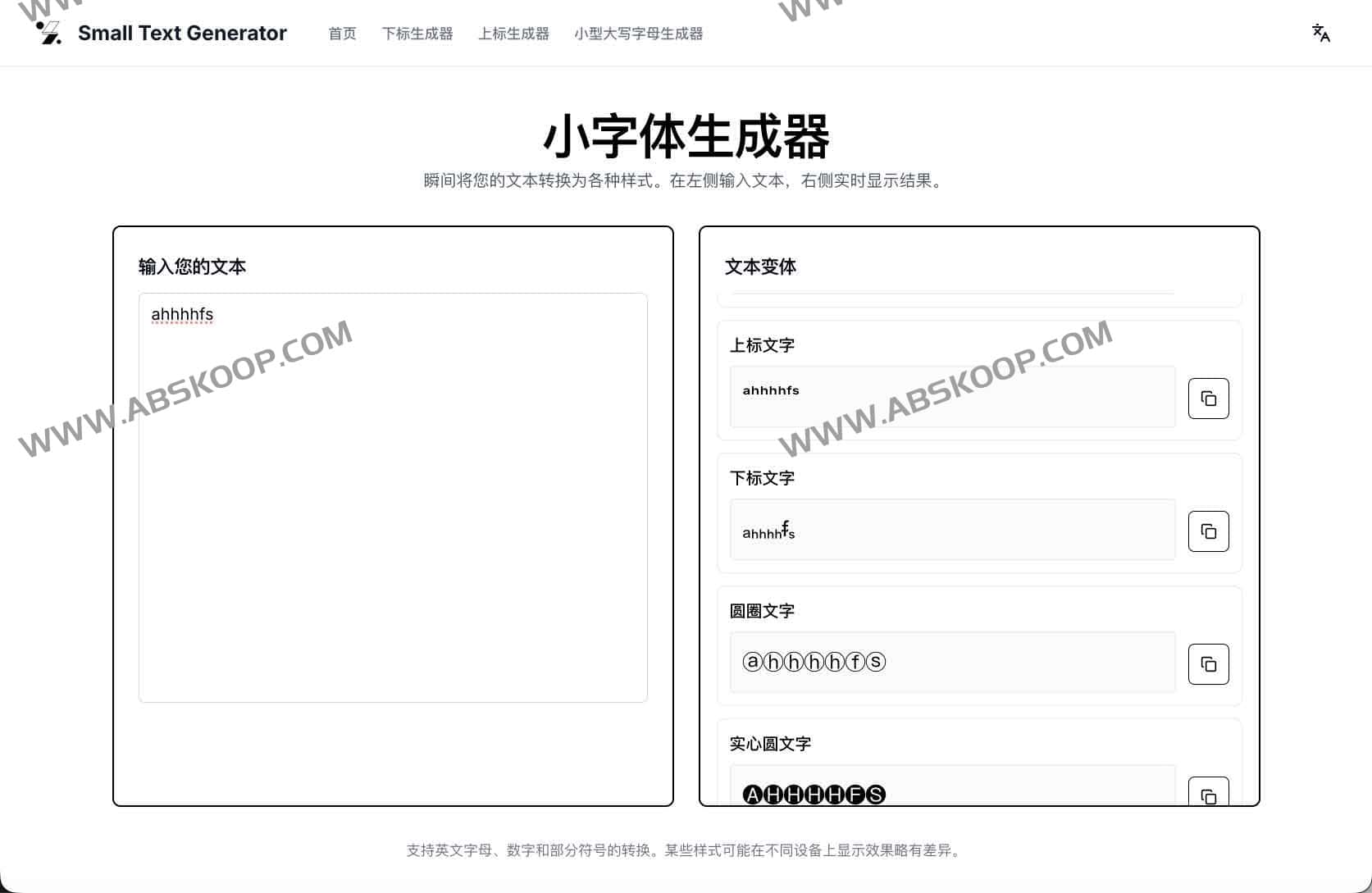
Small Text Generator 是一款基于 Unicode 字符集的免费在线转换工具。它能将普通的英文字母、数字和符号快速转换为各种特殊视觉样式,且无需注册或安装,转换结果可直接复制并粘贴至各类社交平台。
核心能力与特性
• 多样化的样式库 :内置 9 种主流样式,涵盖小型大写字母、上标、下标、圆圈文字、方框文字、花体、粗体、斜体及颠倒文字。
• 零延迟实时预览 :采用即时转换机制,输入文本的同时即可看到所有样式的同步效果。
• 极高的兼容性 :由于生成的是标准 Unicode 字符而非自定义字体文件,因此在不同设备和操作系统间具有极强的通用性。
典型应用场景
• 社交账号个性化 :优化 Instagram 个人主页(Bio)的视觉吸引力,或在 Discord、Twitter 上创建更醒目的用户名。
• 创意文本排版 :在 Reddit 评论中通过风格化文字突出重点,或在博客、演示文稿中使用特殊的小标题特效。
• 数字艺术表达 :利用上标、下标或圆圈文字构建独特的视觉符号与昵称。
技术原理解析
它与传统字体的区别是什么?
该工具并非改变文本的字体(Font),而是将字符替换为 Unicode 标准中定义的相似符号。这意味着你不需要对方安装特定字体,对方在任何支持 Unicode 的设备上都能看到同样的视觉效果。
样式示例:
hello → ʜᴇʟʟᴏ (小型大写)
hello → ʰᵉˡˡᵒ (上标)
hello → ₕₑₗₗₒ (下标)